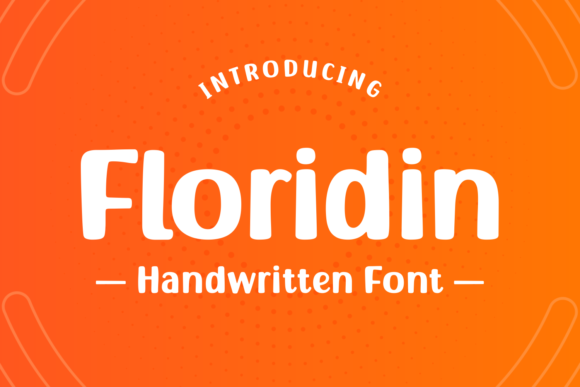
Floridin Font
Floridin Font – لمسة إبداعية وأنيقة لتصاميمك
استمتع بجمالية الخطوط مع Floridin Font، خط أنيق وعصري يجمع بين البساطة واللمسات الفريدة، مما يجعله مثالياً لمختلف أنواع التصاميم. سواء كنت تعمل على تصميم الشعارات، الهوية البصرية، أغلفة الكتب، الدعوات، أو حتى المحتوى الرقمي، فإن هذا الخط سيضيف لمشروعك طابعًا راقيًا وجذابًا.
???? مميزات الخط:
✅ تصميم احترافي وأنيق
✅ مثالي للشعارات والعلامات التجارية